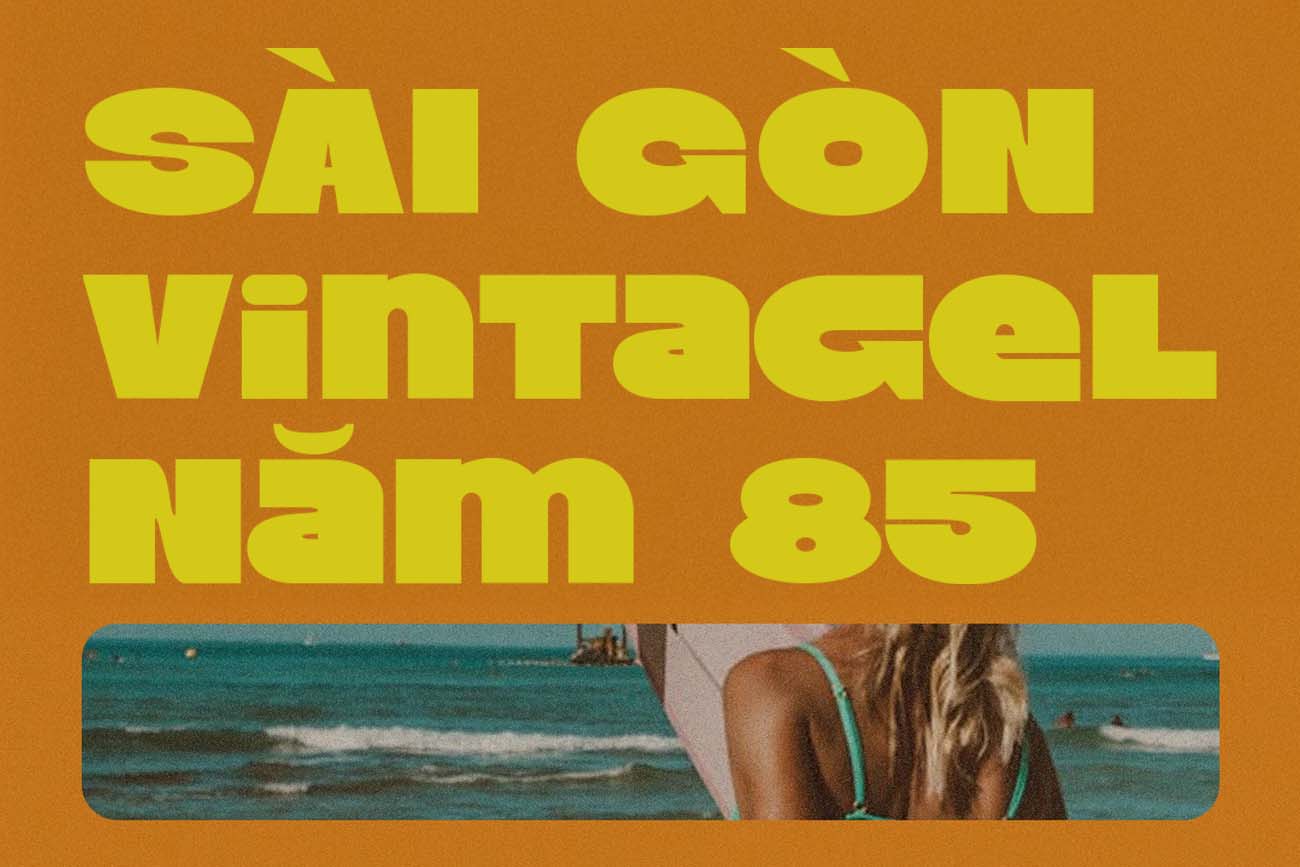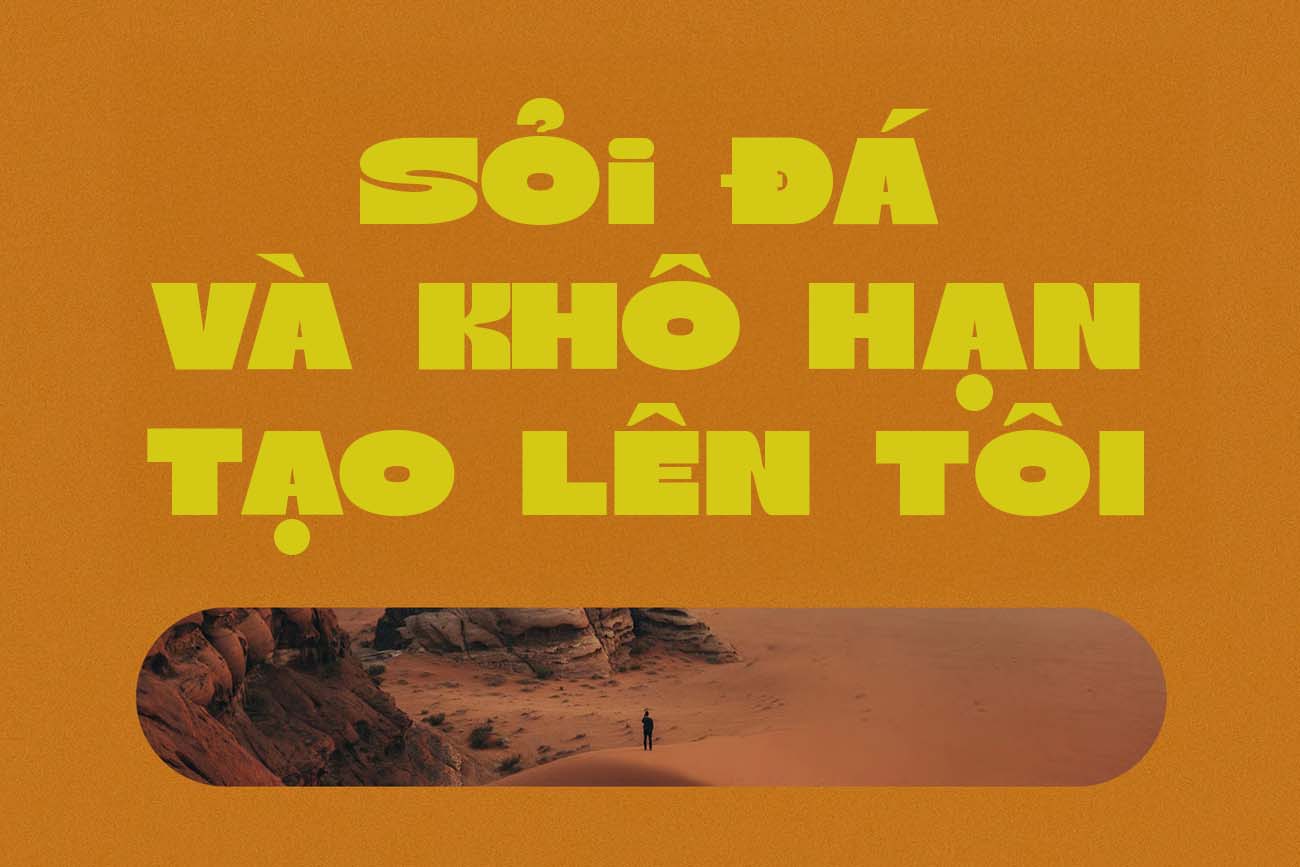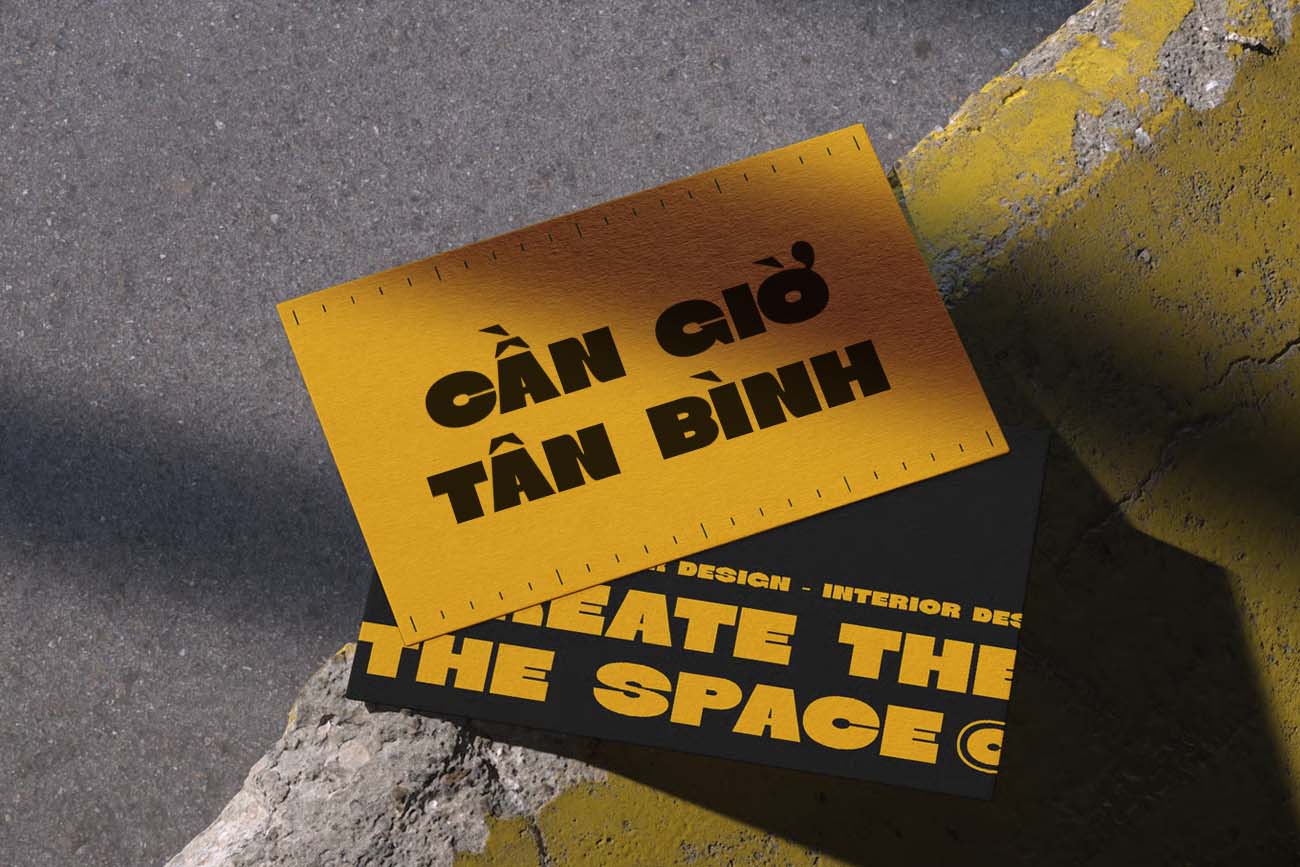
Phông chữ phong cách retro xưa cũ TH Baserio Việt hóa
TH Baserio Bold – Font Chữ Việt Hóa Mạnh Mẽ & Cổ Điển
Baserio Bold Vintage Sans là một font sans-serif mang phong cách retro cổ điển, được thiết kế bởi Sensatype Studio – một đơn vị nổi tiếng với các bộ font hình học mang tính ứng dụng cao. Bộ font này đã được Việt hóa trọn bộ bởi Fontdep.vn, hỗ trợ đầy đủ tiếng Việt và có thể dùng linh hoạt trong nhiều dự án sáng tạo.
Điểm đặc biệt của Baserio Bold không chỉ nằm ở thân chữ dày dặn, vuông vức và cân đối, mà còn ở việc gần như mỗi ký tự đều có glyph thay thế, mang lại sự đa dạng và linh hoạt về mặt hình thái. Điều này giúp các nhà thiết kế dễ dàng tạo nên điểm nhấn riêng cho tiêu đề, logo hoặc banner quảng cáo mà không bị trùng lặp phong cách.
Với cấu trúc in hoa toàn bộ, đường nét sắc sảo và tỉ lệ chuẩn mực, Baserio phù hợp cho các thiết kế logo thương hiệu, poster vintage, bao bì sản phẩm thủ công, hoặc ấn phẩm nhận diện mang phong cách hoài cổ.